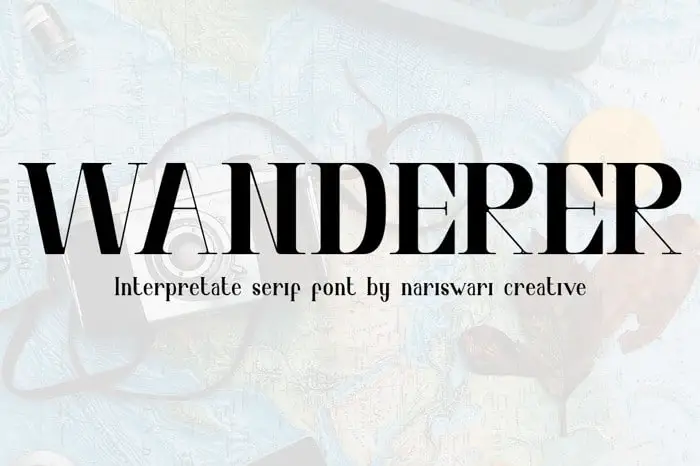
Interpretate Four Display Font – Download Grátis
Descobrimos Interpretate Four Display Font, uma elegante fonte vintage label criada pela Vianor para a 99designs. Esta fonte é perfeitamente adequada para textos e também brilha quando se utiliza como títulos de destaque, logomarcas ou elementos decorativos em projetos visuais. Perfeita tanto para usos cotidianos quanto para criações mais elaboradas, Interpretate Four Display oferece uma ampla variedade de alternativas para letras maiúsculas, que podem ajudar a tornar seus designs mais expressivos e divertidos. Com apenas algumas pequenas modificações no uso desses caracteres alternativos, você pode explorar um vasto conjunto de opções para personalizar seu design. Adicione elementos decorativos à sua fonte e verá como isso complementa o aspecto geral do projeto. Esta fonte não só oferece uma abordagem estilizada e criativa para textos convencionais, mas também permite que você brinque com cores, tamanhos e formatos, proporcionando resultados impressionantes em qualquer aplicação visual.